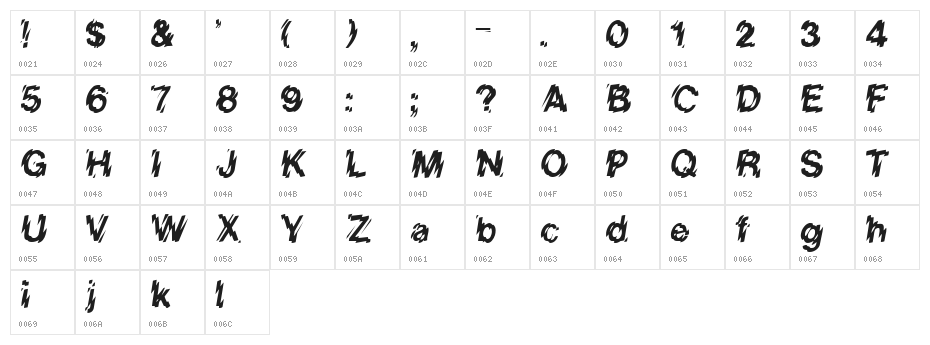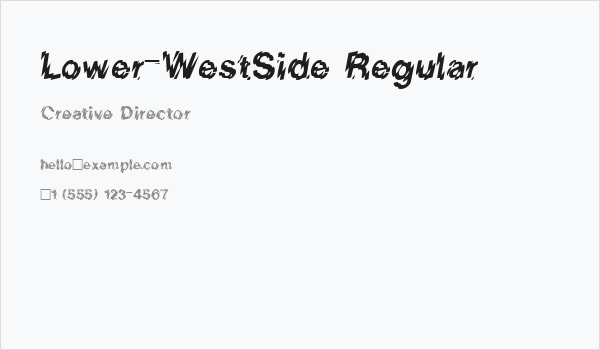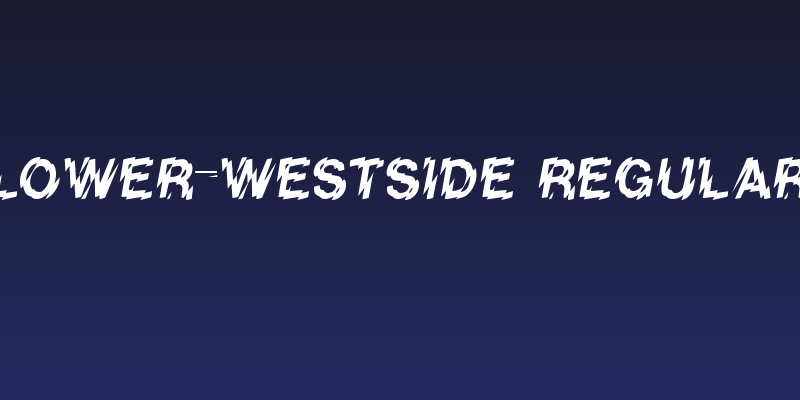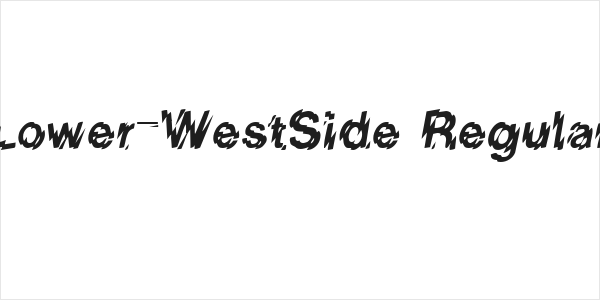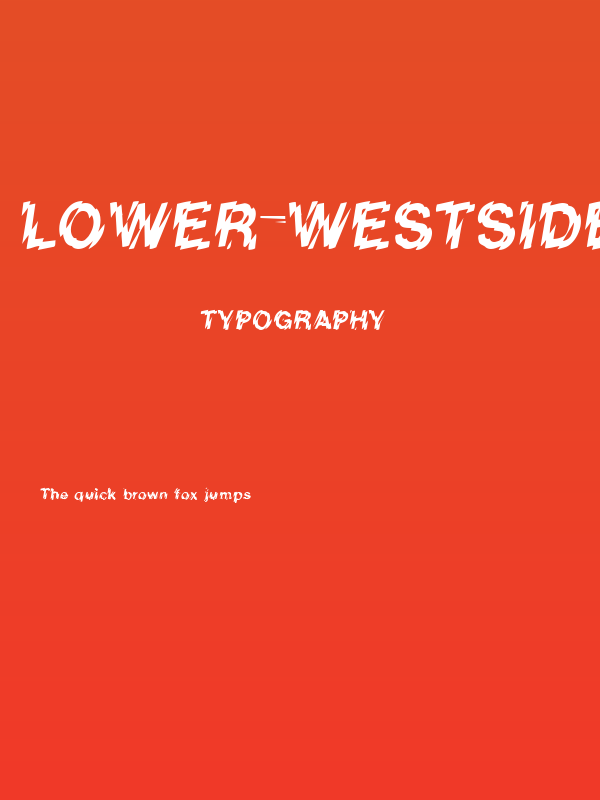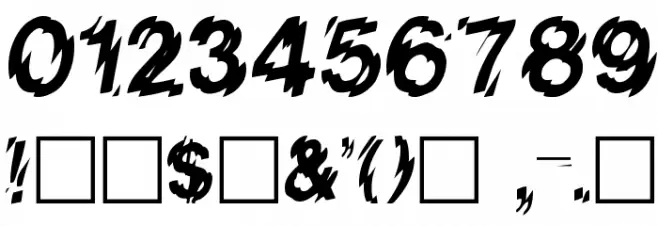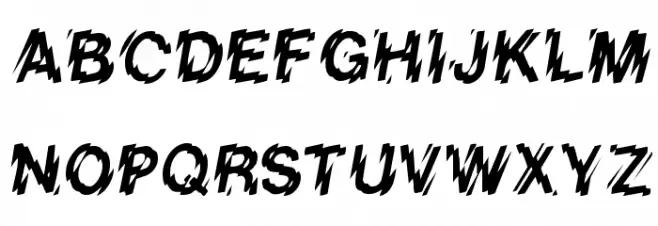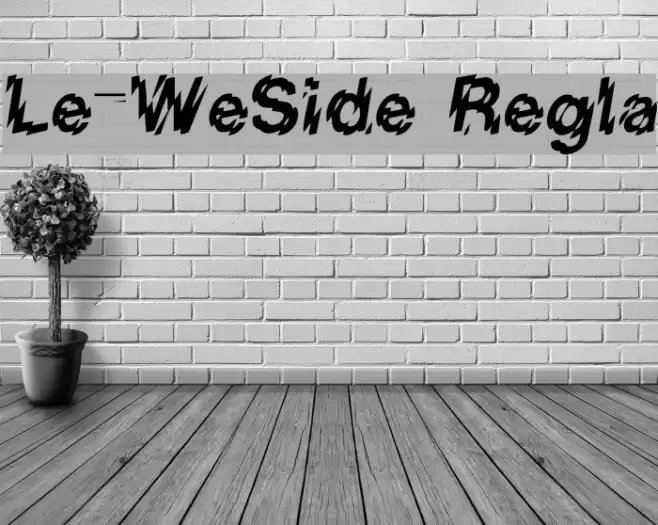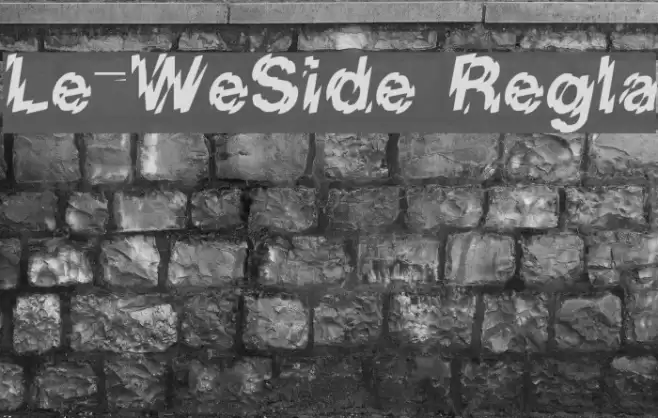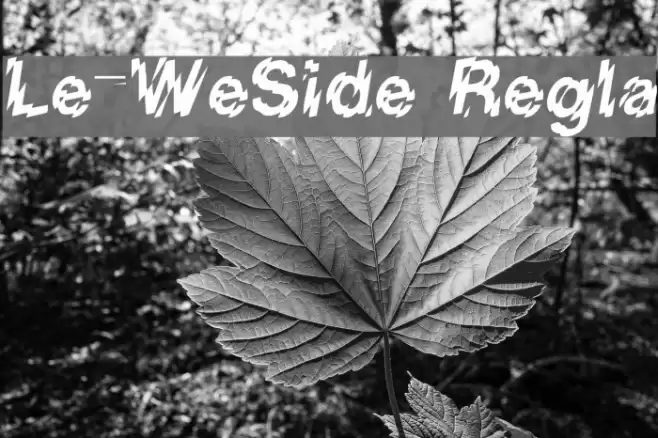
Lower-WestSide Regular Font
| नाम | Lower-WestSide Regular |
| श्रेणियाँ | Broken |
| इटैलिक | Yes |
| कंट्रास्ट | High |
| समग्र शैली | Modern, Edgy |
| उपयोग का मामला | Logos, Headlines, Posters |
| सुझाए गए प्रोजेक्ट | Ideal for music album covers, sports team logos, urban-themed posters, and dynamic branding materials. |